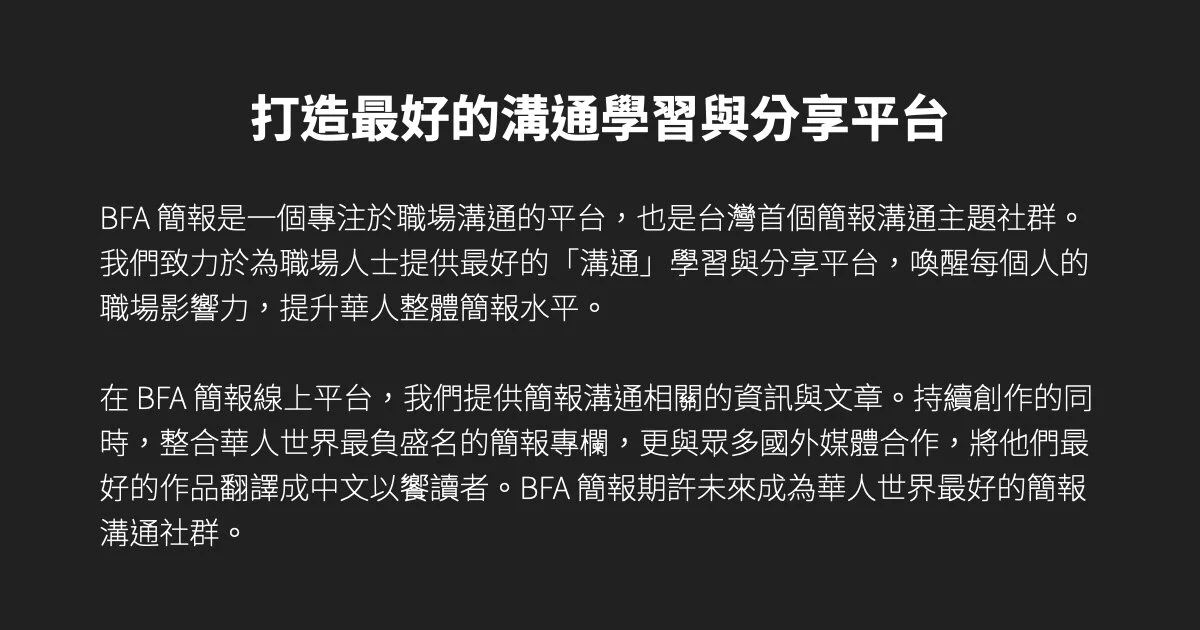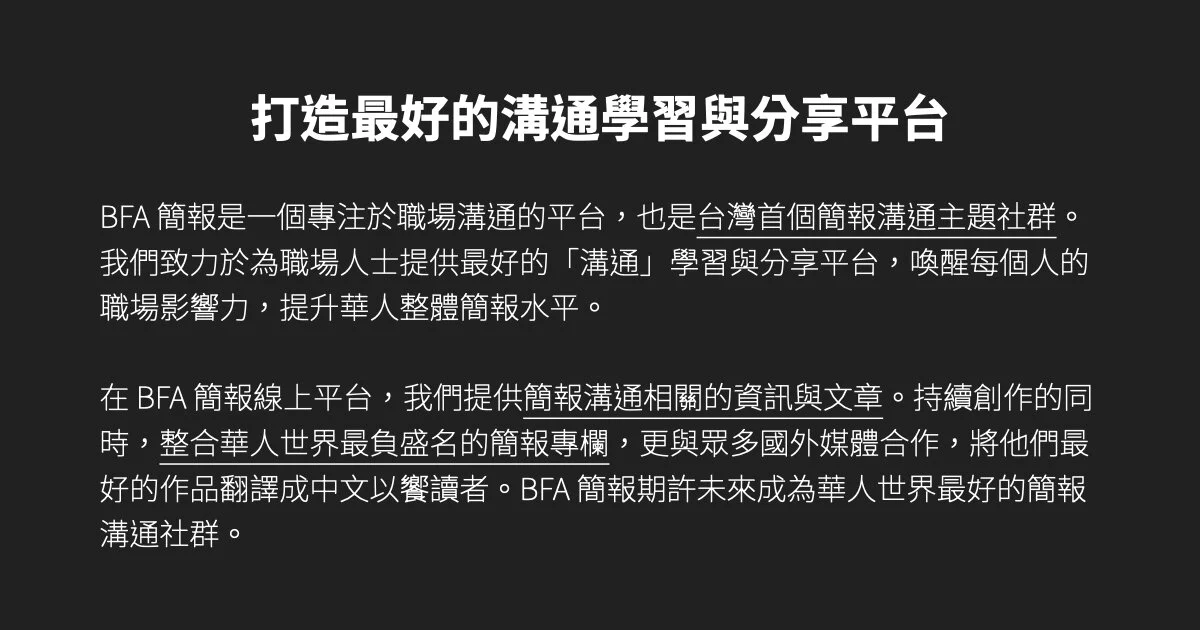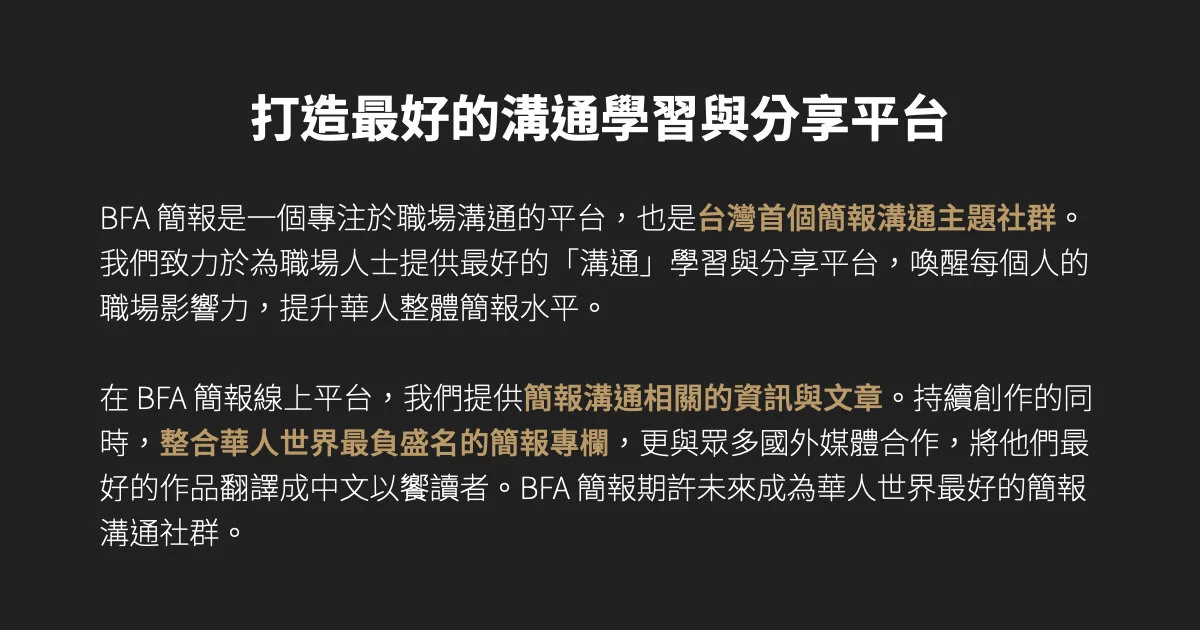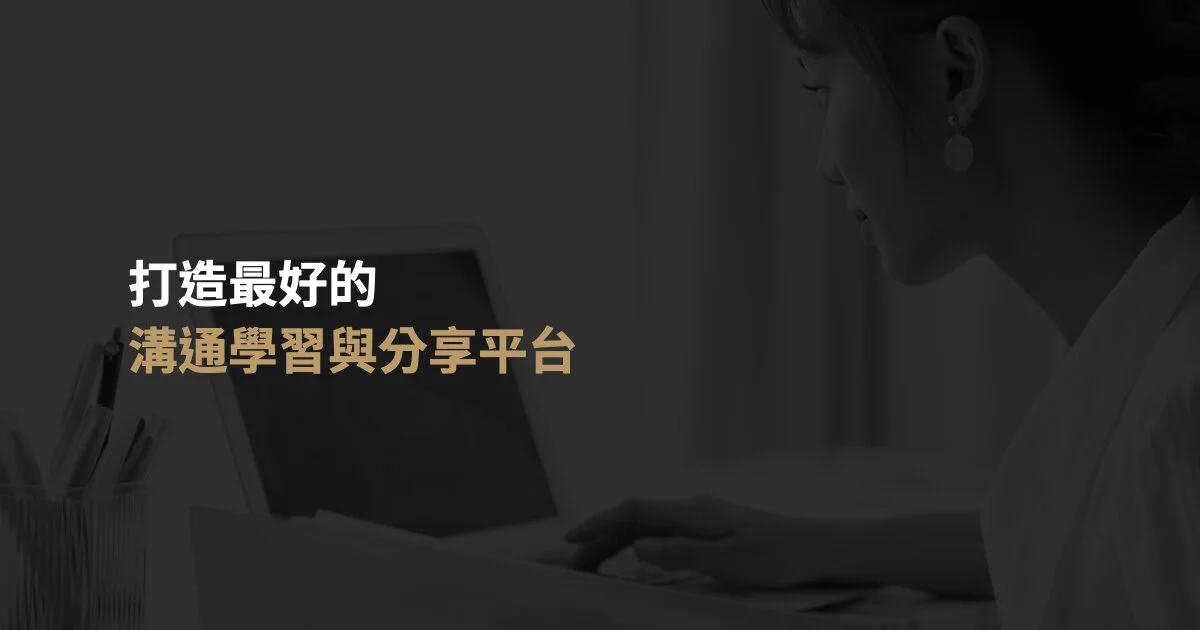
製作簡報時,除了直接套用簡報軟體內建的字型外,我們也可以使用自己下載的字型資源。不過,在使用這些字型前,其實有五個使用原則需要留意。以下將分享簡報字型的五個使用原則,幫助您重新檢視、並優化手上的簡報。
PPT字體的使用原則1:字型選用要符合目的
每種字型都有自己的獨特個性和風格,例如襯線體 (標楷體、宋體) 帶來學術與文藝相關的氣息 ; 非襯線體 (思源黑體、微軟正黑體) 能有效襯托出科技、數位與現代感。若使用不符合簡報目的的字型,不僅會讓觀眾失焦,也會讓簡報失去想傳達的風格。舉一個極端的例子,在專業的學術簡報中,使用娃娃體字型。
推薦簡報適用字體「思源黑體」,不僅免費可商用,其俐落、充滿現代感的線條,相當適合使用在專業內容的呈現上。
Before : 使用了不符合簡報目的的字型
After:使用符合簡報目的的字型
PPT字體的使用原則2:整份簡報的字型不超過三種
在簡報中維持風格的一致性不是難事,除了用色和圖片素材的選用,字型也是維持一致性的重要元素。我們可以將整份簡報視為一個主體,在簡報中使用的字型盡可能不超過三,甚至只使用一種字型會更好。因為在同一份簡報中使用過多不同種類的字型,會讓簡報看起來不夠專業,甚至有拼貼拼湊的感覺。
PPT字體的使用原則3:運用字體的粗細變化強調重點
若想要在簡報中強調重點,不建議使用斜體、底線或螢光筆的效果,因為斜體、底線會讓投影片看起來風格雜亂,不僅會影響整體設計的美感,也會讓觀眾分心。
所以,比較適當的做法,是運用字體本身的粗細變化,例如在重要的段落或字句使用粗體,並搭配企業或單位識別色,就能讓觀眾第一眼就看到重點。
Before : 使用底線或斜體字,會讓投影片看起來雜亂
After : 運用字體粗細變化與企業識別色,有效強化出重點
PPT字體的使用原則4:掌握基本的對齊
在簡報設計中,對齊是基本功夫,不僅能讓畫面看起來乾淨整齊,也能降低觀眾在閱讀資訊的難度。同樣的,文字排版也是如此,除了對齊之外,也可以適當的依語意斷行,幫助觀眾在閱讀上更容易理解。
PPT字體的使用原則5:考量閱讀動線
簡報的投影片尺寸已從過去的 4:3,轉變為 16:9,甚至有超 16:9 的特殊版型。也因為數位時代下閱讀載體的改變,我們的視覺動線已從「由上至下」轉變為「由左至右」的 Z 字型閱讀動線。
回到簡報的文字排版設計,只要掌握視覺動線由左至右的基本原則,例如讓文字框的位置靠左,在視覺上將會更為平衡。
Before : 文字框重心偏右,帶來視覺上的不平衡
After : 文字框靠左對齊,滿足由左至右的閱讀動線
中文字型推薦 - 思源黑體 : Adobe 與 Google 聯合開發,醒目、現代,帶有俐落的感覺,有八種字體粗細變化,適合各類商務情境簡報的使用。
英文字型推薦 - Goldman Sans : 為高盛集團釋出的字型,線條乾淨,充滿現代感,特別針對數位金融需求所設計,即使數字細小也能輕易閱讀。